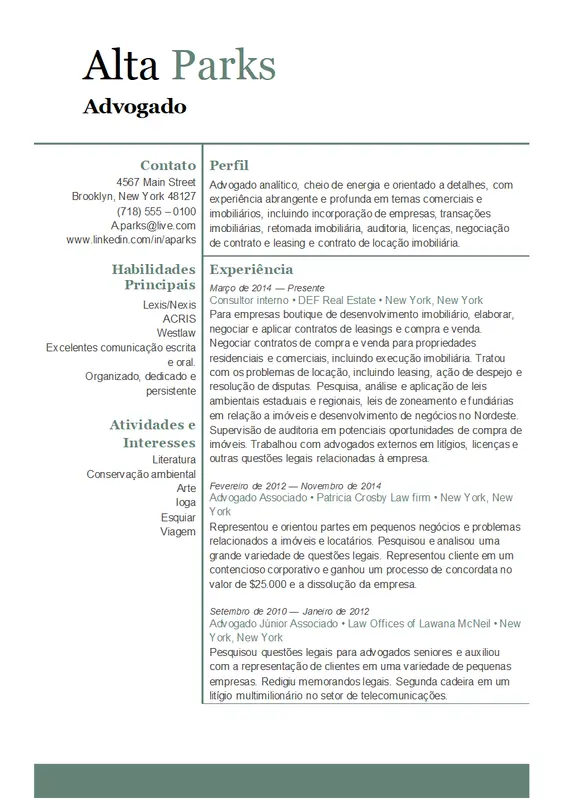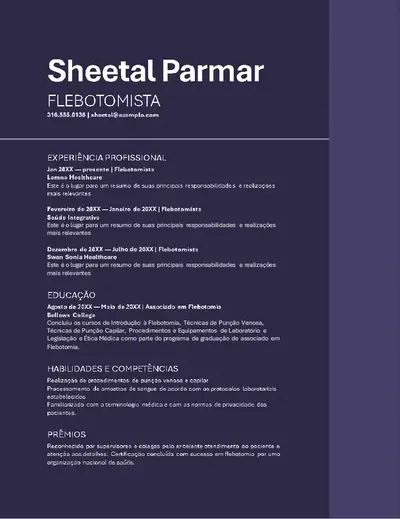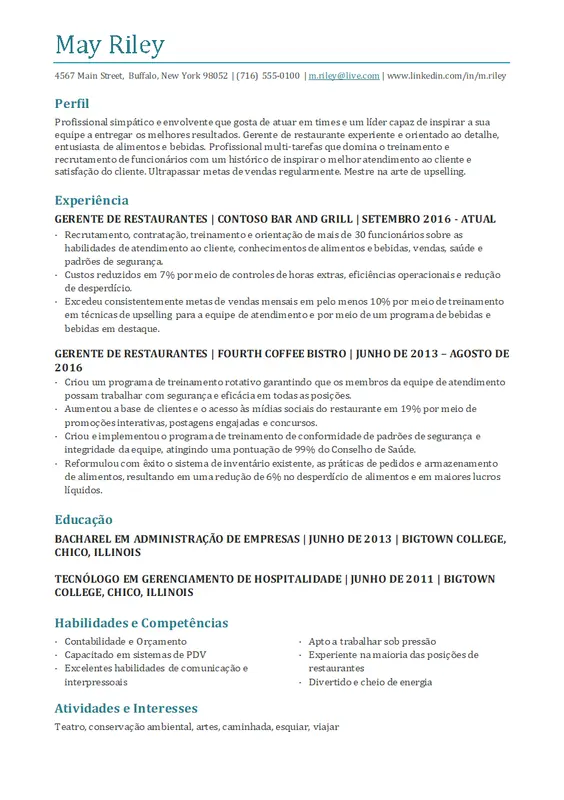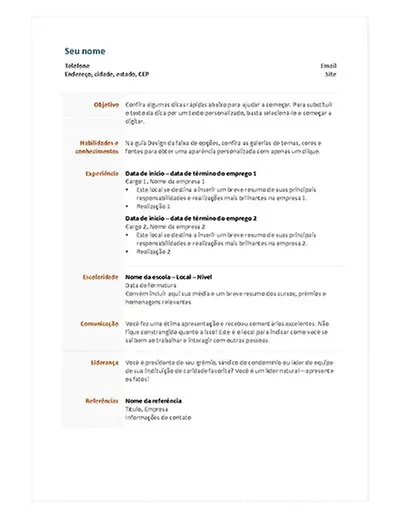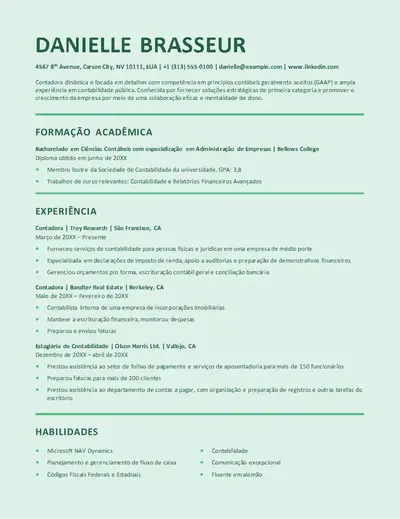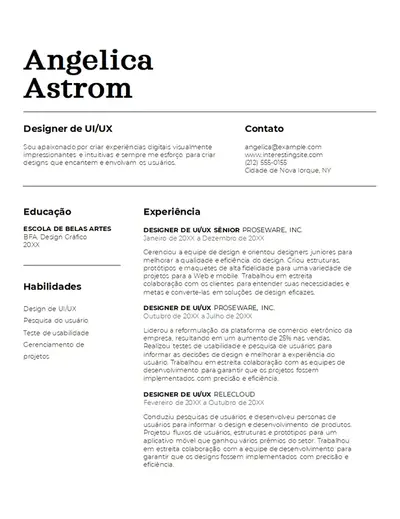
Escolher a fonte certa para o currículo é uma das maneiras mais eficazes de causar uma primeira impressão forte. As fontes podem comunicar credibilidade e personalidade, apoiar o profissionalismo e refinar um currículo para refletir a atenção aos detalhes.
Comece com um currículo bem elaborado com dicas práticas sobre como escolher estilos e tamanhos de fonte apropriados. Saiba como criar uma hierarquia de fontes clara, aplicar formatação de forma consistente e criar um currículo refinado no Microsoft Word.
As seis melhores fontes de currículo para qualquer candidatura a emprego
A melhor fonte de currículo faz mais do que ter uma boa aparência na página. A escolha da fonte molda como um currículo é lido, classificado e lembrado. Aqui estão as principais fontes de aparência profissional perfeitas para criar um currículo, todas disponíveis no Microsoft Word.
1. Fonte Calibri
Uma fonte sans serif moderna, a Calibri se tornou o padrão ouro corporativo. Simples de ler, Calibri exala profissionalismo e autoridade. Com estilos arrojados e leves, esta fonte sem serifa é facilmente adaptável para se adequar a qualquer impressão. Ótima opção para carreiras como direito, finanças e saúde, a Calibri se adapta a qualquer função em que uma aparência limpa e profissional seja a prioridade.
2. Fonte Garamond
Uma fonte serif clássica, a Garamond é uma escolha confiável em publicação profissional e documentos formais. A fonte é fácil de ler em tamanhos menores, dando ao currículo uma aparência autoritária e refinada. Garamond é uma boa escolha para funções acadêmicas, editoriais, jurídicas e cargos executivos, onde uma apresentação tradicional e de alta credibilidade é valorizada.
3. Fonte Montserrat
Montserrat traz um visual limpo e acessível para um currículo. Uma fonte ideal para publicidade impressa e placas de rua urbanas, Montserrat é uma escolha natural para currículos em áreas criativas, bem-estar e imóveis. Essa fonte sem serifa tem uma sensação ousada, ao mesmo tempo em que é extremamente clara e digitalizável.
4. Fonte Candara
Candara é uma opção sutilmente elegante que parece polida sem ser excessivamente formal. Fácil de ler com um estilo distinto, essa fonte é adequada para currículos com menos texto, como um e funciona especialmente bem para funções de estágio, software e TI.
5. Fonte Cambria
Cambria é uma fonte serif tradicional e balanceada que transmite confiabilidade e profissionalismo. Projetado para fácil leitura na tela (opens in a new tab) em tamanhos de texto pequenos, Cambria é uma opção sofisticada que se adapta a qualquer currículo. Essa fonte com serifa funciona bem para funções de gestão, recursos humanos e liderança, e é uma ótima opção para currículos de engenharia e arquitetura, pois o design suporta símbolos de matemática e ciências.
6. Fonte Aptos
Aptos é a fonte padrão no Microsoft Word e no Microsoft 365 que equilibra o estilo contemporâneo com uma forte legibilidade para criar um currículo claro e digitalizável. Projetado para legibilidade em telas modernas com um tom mais quente e neutro, Aptos (opens in a new tab) é uma fonte sans serif flexível que se adapta em títulos e corpo de texto. Essa fonte contemporânea é adequada para aplicativos de tecnologia, saúde e gerenciamento.
7. Fonte Arial
Arial é uma fonte sans serif limpa e direta que dá ao currículo uma aparência profissional e fácil de digitalizar. Sua flexibilidade o torna uma escolha prática para currículos em todas as funções e estágios de carreira, sejam compartilhados digitalmente ou impressos. Essa fonte elegante e consistente é particularmente compatível com aplicativos corporativos, voltados para o cliente e focados nos negócios.
Como escolher uma fonte de currículo profissional
Com uma lista restrita de fontes adequadas selecionada, a próxima etapa é encontrar a correspondência certa para o Candidatura a emprego. Escolher a fonte certa com base na função e no nível de antiguidade envolve entender as nuances culturais e profissionais de cada setor de trabalho, bem como a impressão que ela precisa causar nos empregadores em potencial. Veja algumas diretrizes para ajudar a encontrar a melhor fonte.
Considere a função e o nível do trabalho
Diferentes funções de trabalho e níveis de antiguidade podem influenciar o quão criativo ou formal um design e fonte de currículo devem ser. Considere o nível de antiguidade da função, nível básico, nível médio ou sênior, pois isso determina quanta liberdade criativa a escolha da fonte pode exigir.
Por exemplo: a Calibri pode dar a um currículo uma aparência limpa e profissional para uma função de gestão, enquanto a Montserrat pode adicionar uma sensação mais contemporânea para funções em áreas criativas.
Considere o campo de trabalho
Cada profissão e campo de trabalho vem com seu próprio conjunto de valores e expectativas. Currículos criados para áreas formais de trabalho, como direito, medicina, governo e finanças, devem transmitir confiabilidade e profissionalismo, portanto, fontes como Aptos e Calibri são um ajuste natural.
- Como editar o tipo de letra e tamanho do tipo de letra de um currículo no Word?
Abra um currículo no Word, selecione o texto a atualizar e utilize o menu pendente Tipo de Letra no separador Base para escolher um novo tipo de letra. Ajuste o tamanho do texto utilizando o campo de tamanho do tipo de letra ao lado. Para atualizar todos os cabeçalhos ou corpo de texto ao mesmo tempo, clique com o botão direito do rato no estilo relevante na galeria de estilos e selecione modificar. A alteração aplica-se automaticamente a todo o documento. Para obter mais formas de editar e formatar documentos no Word, explore editor de documentos.